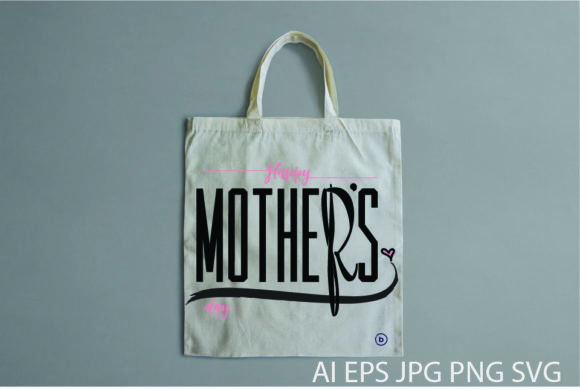
Mothers Day Typeface Mother
適切なデザイン要素を見つけるのは難しい場合がありますが、Mothers Day Typeface Motherは作品を即座に引き立てる優れたコレクションを提供します。
POD(オンデマンド印刷)製品、結婚式の招待状、またはソーシャルメディアのグラフィックを作成している場合でも、Mothers Day Typeface Motherは理想的です。